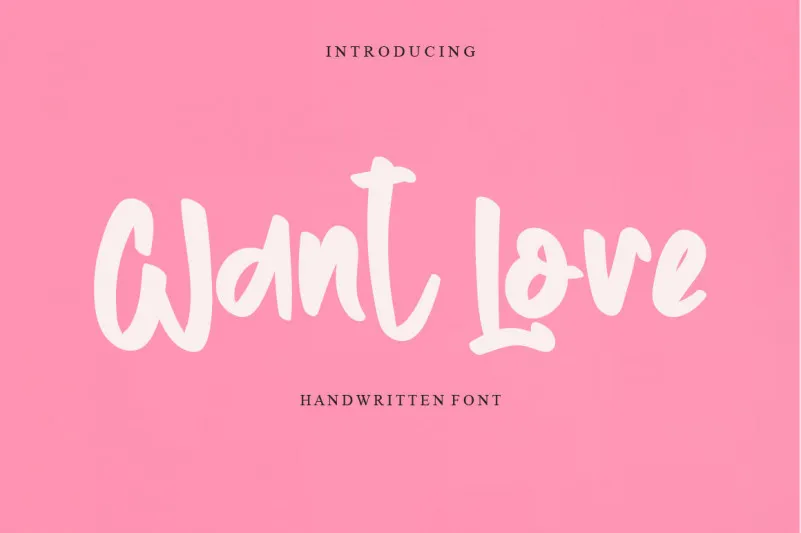
Want Cove Font – Fonte Grátis
Want Cove Font
Aqui está uma descrição para a página de download da font ‘Want Cove Font’ no formato solicitado: ‘Selecionar a ‘WANT COVE Font’ é escolher mais do que apenas uma nova maneira de escrever – você adquire um poder criativo inigualável, prático e amigável. Esta elegante fonte feita à mão transmite um toque único e divertido, ideal tanto para usar em projetos DIY quanto para decorar postagens no Instagram. Com sua tipografia cheia de vida e agradável escrita à mão, ‘WANT COVE Font’ pode transformar qualquer pensamento original em arte real. Este é o recurso perfeito para quem quer dar um toque diferenciado aos seus projetos gráficos, seja na preparação de slides ou no design dos seus perfis nas redes sociais. Seja você designer gráfico, blogueiro digital ou simplesmente alguém que adora fazer coisas únicas e criativas em casa – ‘WANT COVE Font’ é uma escolha inteligente para aqueles que querem deixar suas ideias mais expressivas e atraentes.’